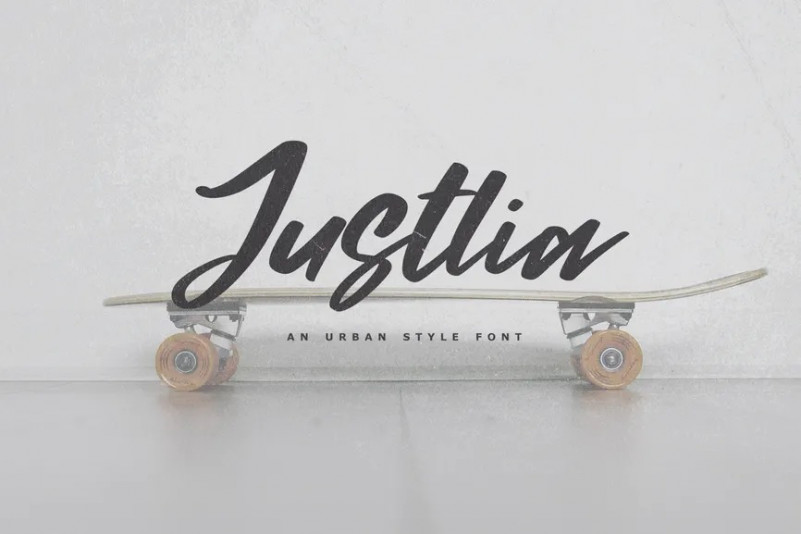
Justlia Font
Justlia – Une police de style urbain, chaque lettre a été soigneusement conçue pour rendre votre texte magnifique. Elle est parfaite pour les Logos, les cartes nominatives, les mises en page de magazines, les invitations, les en-têtes, ou même les œuvres d’art à grande échelle.